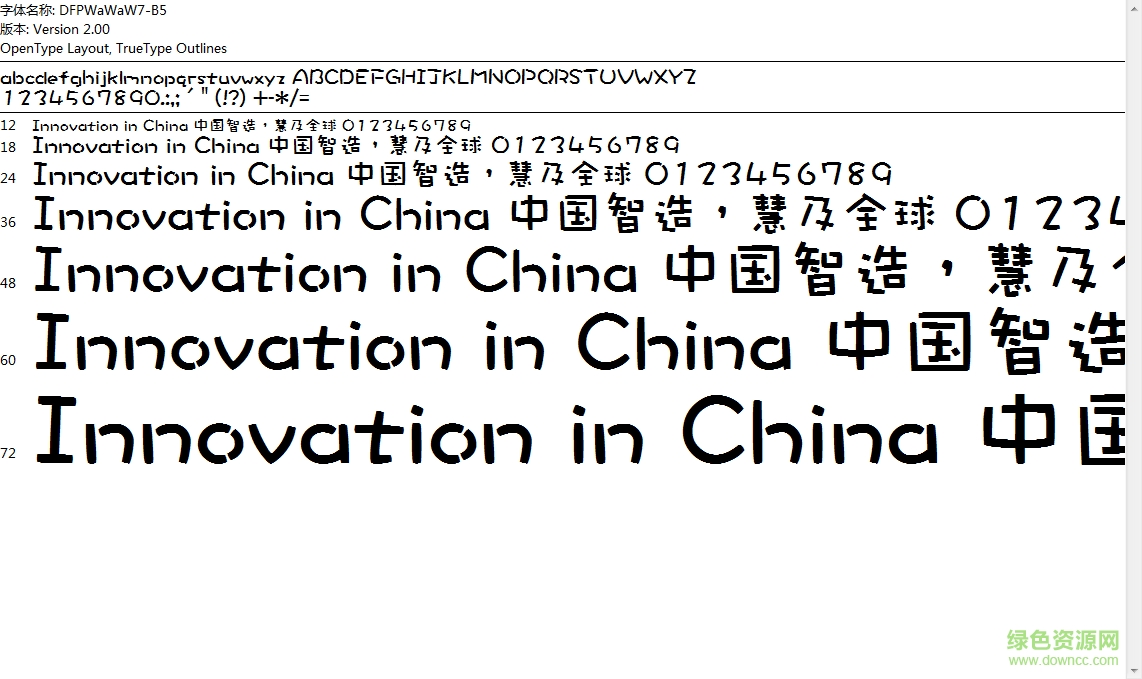
華康娃娃體W7是一款比較可愛的藝術(shù)字體,此款字體采用卡通風(fēng)格,字型線條簡(jiǎn)潔,非常美觀,廣泛應(yīng)用于廣告設(shè)計(jì)、平面設(shè)計(jì)、動(dòng)漫設(shè)計(jì)等領(lǐng)域,需要的朋友歡迎來(lái)綠色資源網(wǎng)下載!